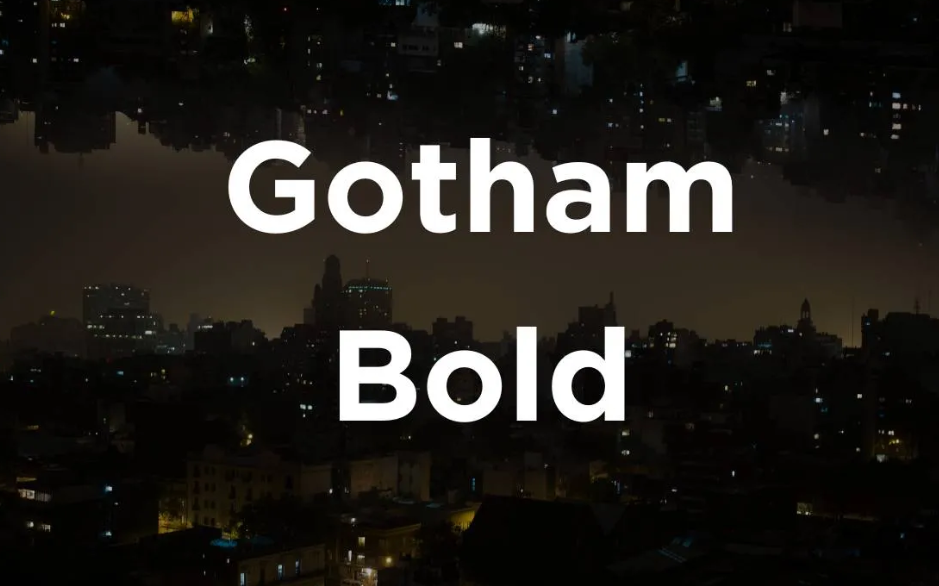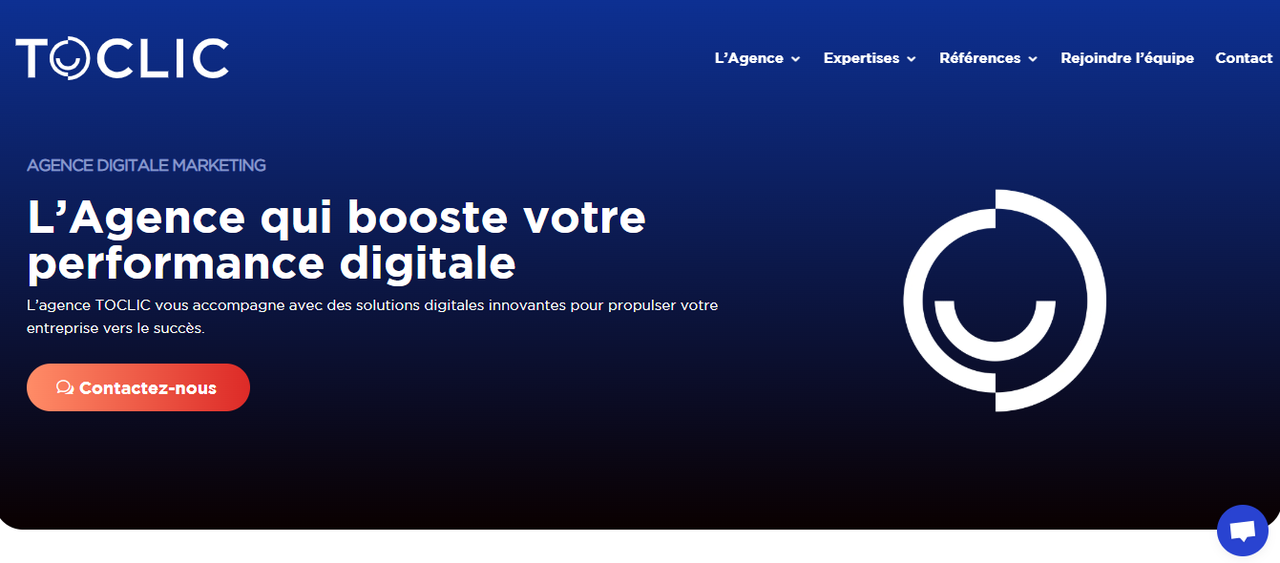
Fon Gotham telah menjadi ruji untuk pereka kerana serba boleh dan reka bentuknya. Dalam artikel ini, kami telah menyenaraikan fon Gotham terbaik dan 6 alat fon Gotham teratas, seperti CapCut. Terokai fon Gotham dengan alatan ini mulai sekarang!
Fon Gotham ialah pilihan popular untuk kerja reka bentuk yang bersih, menambahkan daya tarikan profesional pada reka bentuk anda. Artikel ini memperkenalkan 6 platform teratas dari mana anda boleh memuat turun fon Gotham dengan mudah, seperti CapCut, DeeFont, DaFont dan Behance. Kami juga memperkenalkan sepuluh gaya fon Gotham untuk anda. Semak mana yang terbaik untuk kerja anda!
Apakah fon Gotham
Fon Gotham ialah muka taip sans-serif yang direka oleh Tobias Frere-Jones pada tahun 2000. Ia popular kerana reka bentuknya yang moden dan sangat boleh dibaca, menjadikannya pilihan yang popular untuk pelbagai kesan reka bentuk. Selain itu, kepelbagaian fon membolehkan ia digunakan dalam media yang berbeza, seperti percetakan dan reka bentuk web. Oleh kerana penampilannya yang berani dan luar biasa, ia biasanya digunakan dalam pengiklanan.
Ciri-ciri fon Gotham
• Reka bentuk geometri: Ia mengandungi reka bentuk yang bersih dengan perkadaran yang seimbang.
• Pelbagai berat: Ia tersedia dalam berat yang berbeza, dari nipis hingga tebal.
• Kelayakan tinggi: Ia mudah dibaca dalam saiz yang berbeza.
• Moden dan anggun: Ia menawarkan rupa kontemporari dengan nada profesional.
• Bulat dan terbuka: Ia mempunyai sudut bulat, yang meningkatkan kebolehbacaan.